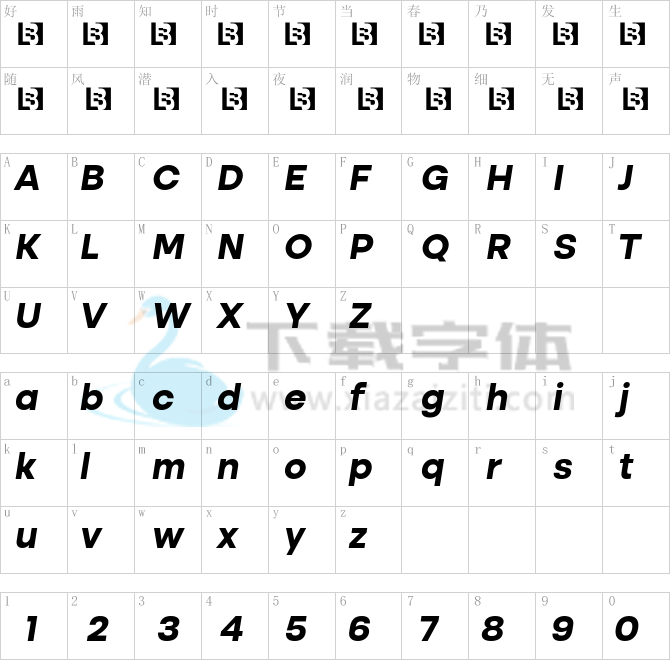
Altone Trial.ttf字体下载,这款字体结构工整、笔画清晰,兼顾美观与易读性,适用于标题、正文、海报、包装、LOGO 等多种场景。字形优雅稳定,风格百搭耐看,适配日常排版与创意设计,让文字呈现更舒适、更具质感。Altone Trial.ttf字体下载一笔一画,皆是细节,以均衡的比例、流畅的线条打造舒适视觉体验,字形端正大气,风格简约现代。无论是商业设计、品牌宣传还是日常排版,都能轻松驾驭,让文字更有格调与力量。Altone Trial.ttf字体下载字体下载。